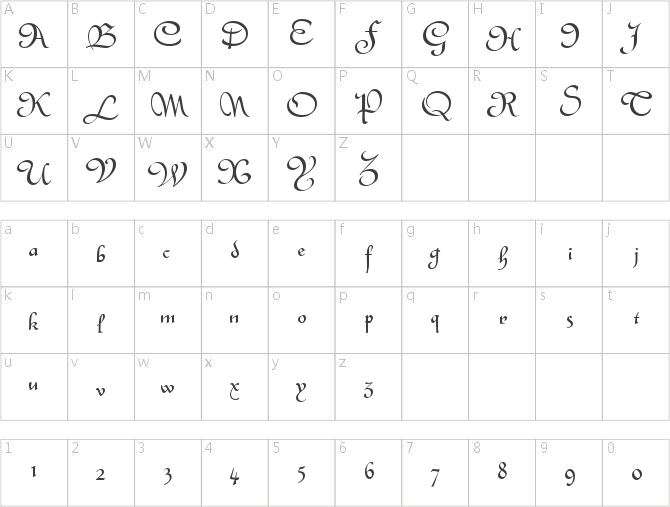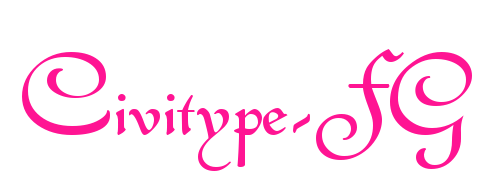
Civitype-FG 詳情頁
字體名稱: Civityp
Civitype-FG
Civitype-FG介紹
Civitype-FG字體字庫是一款讓人賞心悅目、百看不厭的英文字體,適合各類廣告和產品包裝設計應用,字體大小0.06MB,格式為ttf字體,上傳用戶是素年錦時,作者/版權方為未知
Civitype-FG效果圖